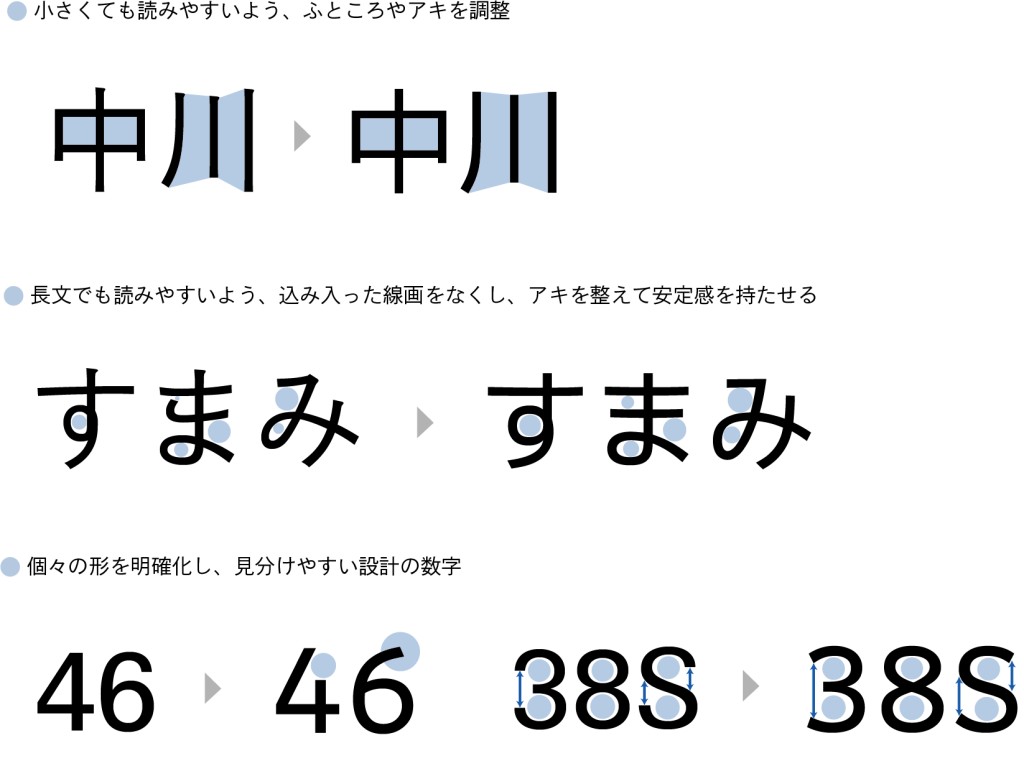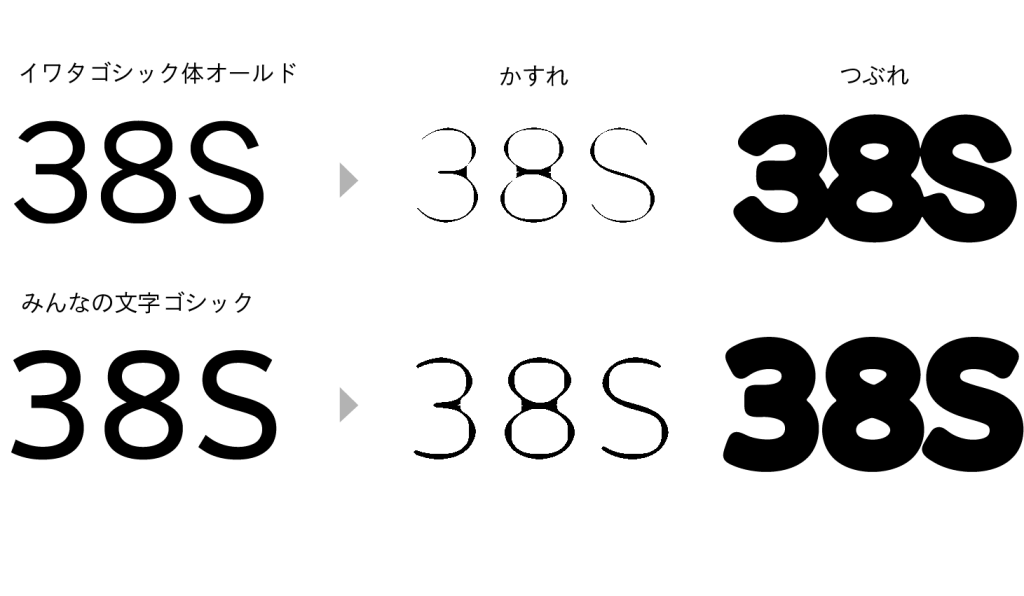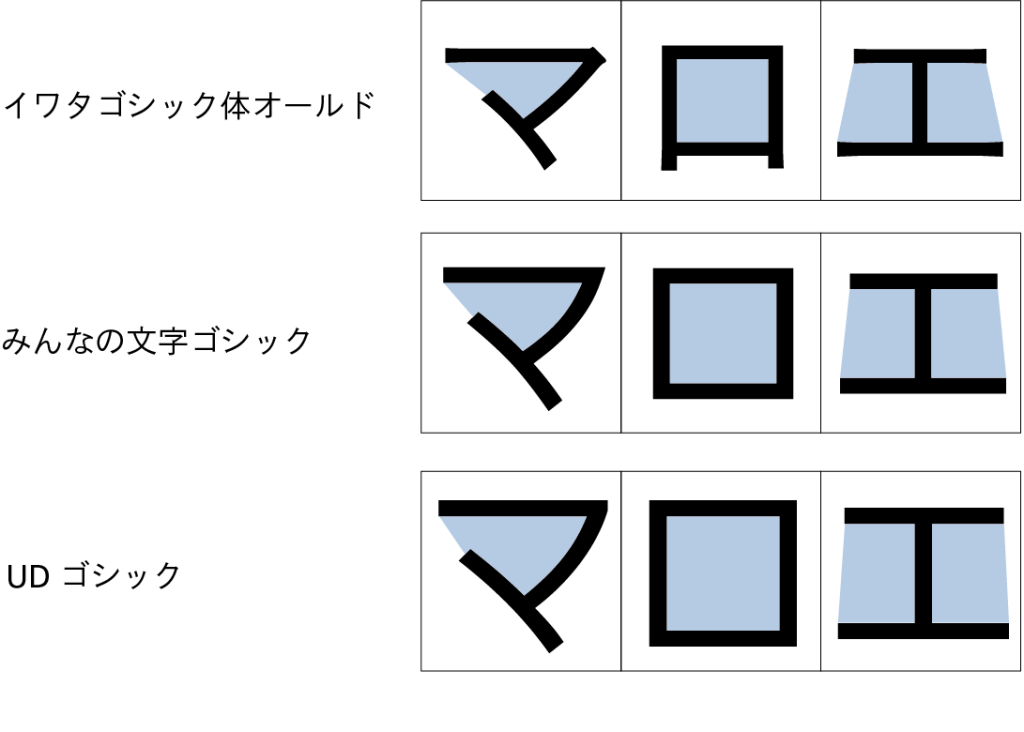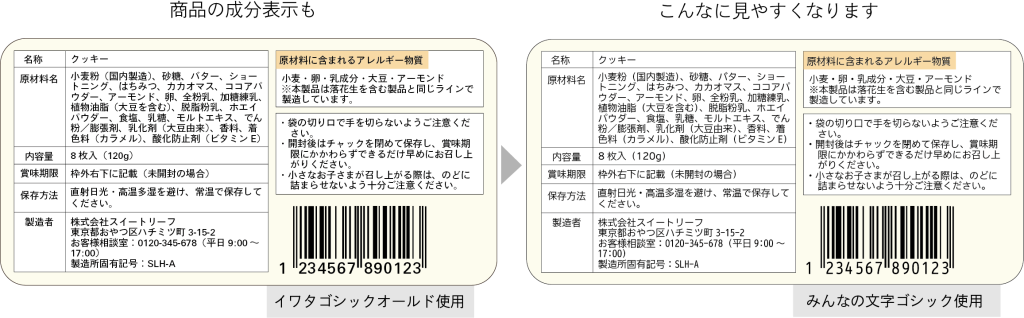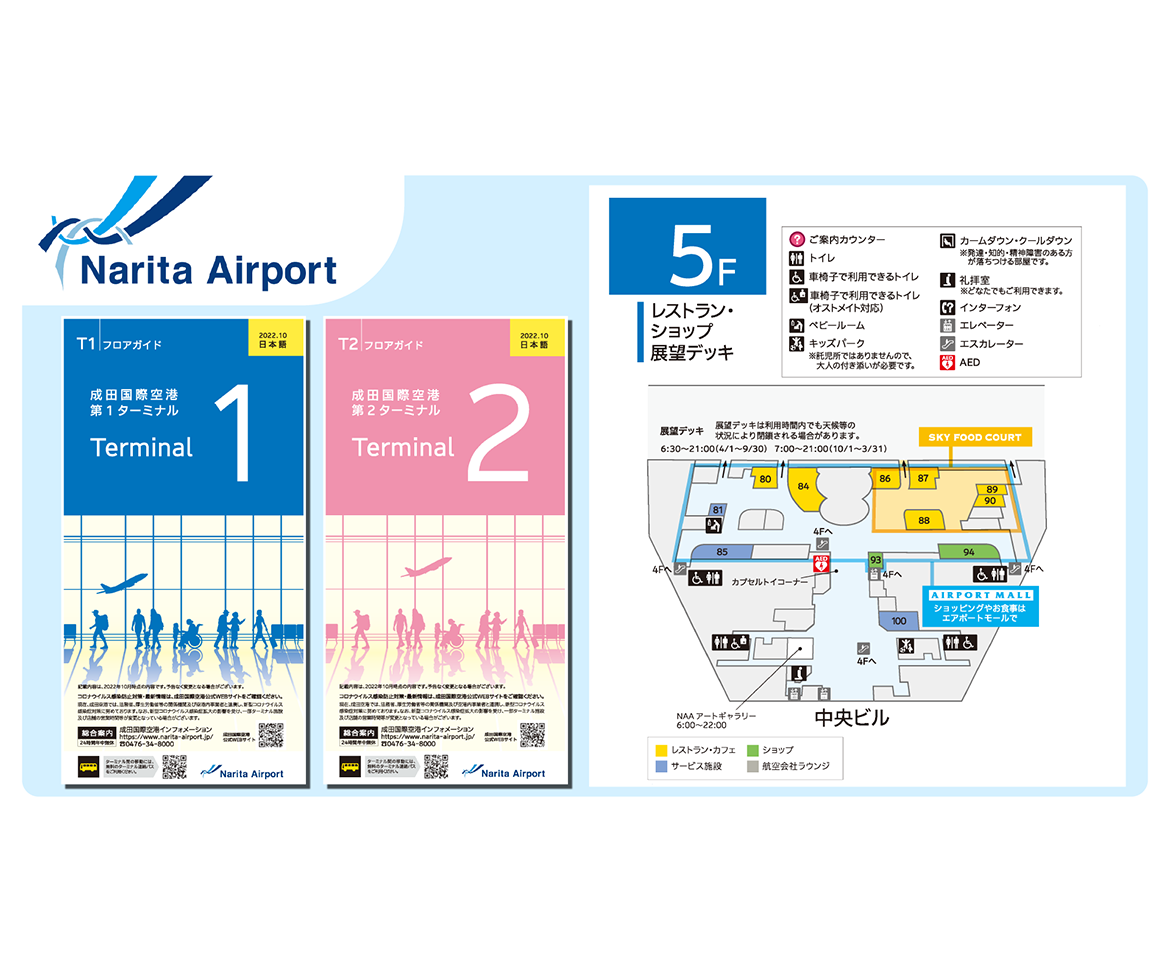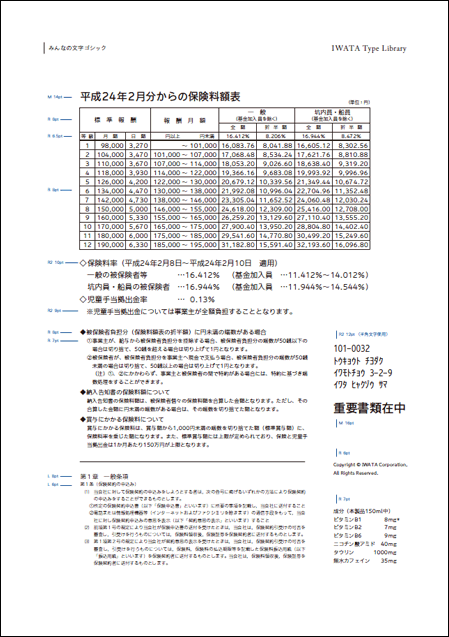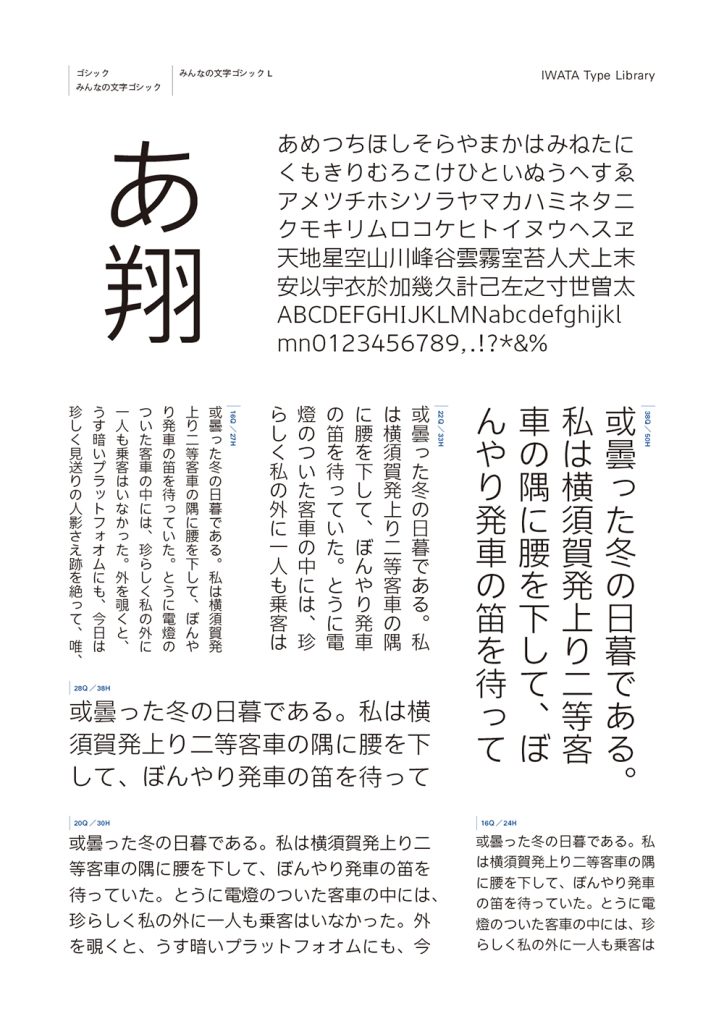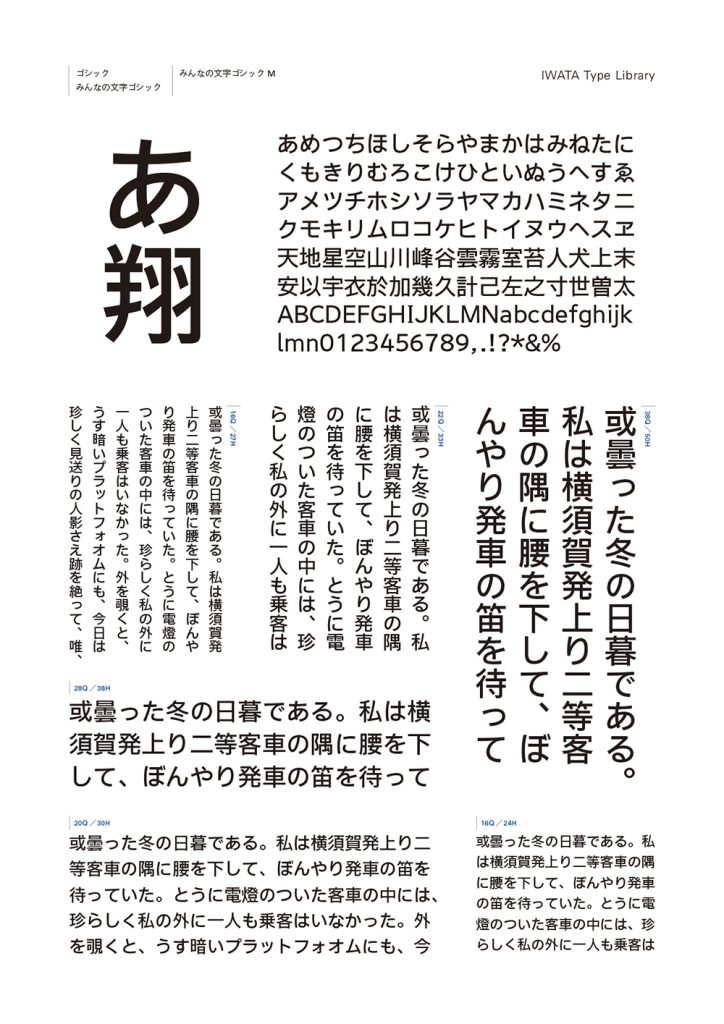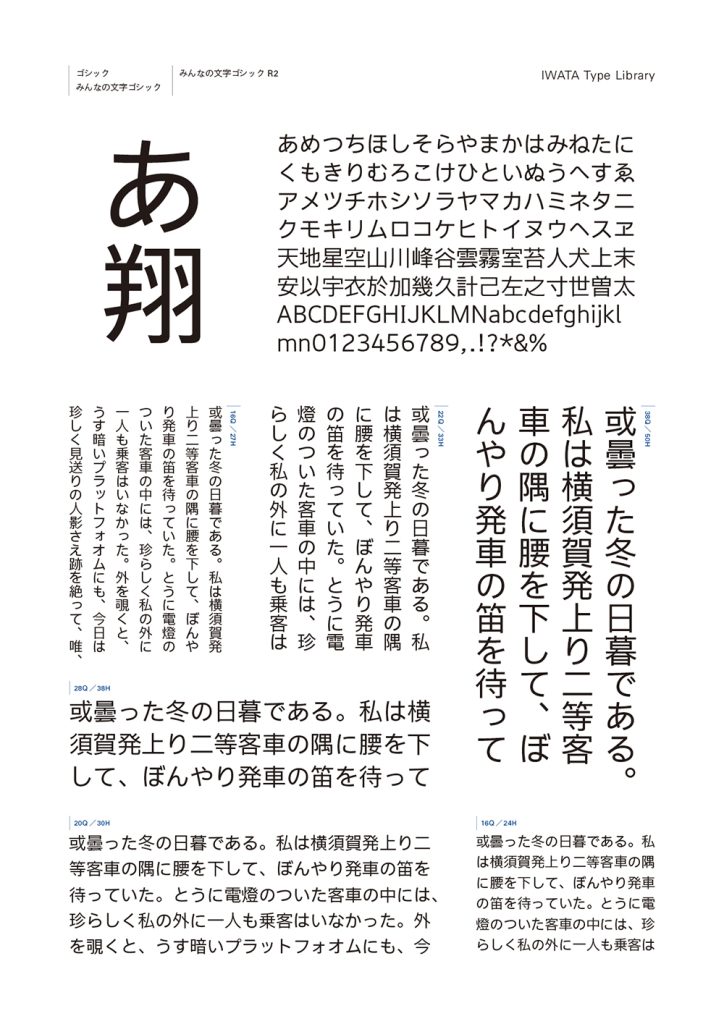
帳票や約款など、小さな文字で情報を伝える書類を読みやすくするために開発されたユニバーサルデザイン(UD)のゴシック体です。UD フォントとして唯一、第三者機関による読みやすさの認証「UCDA 認証」を取得しています。一般社団法人ユニバーサル コミュニケーション デザイン協会(UCDA)、電通、イワタの3 社共同で開発しました。
書体デザインのポイント
つぶれ・かすれ・低解像度などの劣化した環境に強く、大事な情報の誤読を防ぎます。加えて、大きくデザインしすぎないことで可読性も確保し、さまざまなシーンや幅広い年齢に対し読みやすさを維持できます。
※「イワタゴシック体オールド」と「みんなの文字ゴシック」を比較しています
開発時は、読みやすさを客観的に判断するために人間中心設計(HCD)プロセスを採り入れ、ユーザー評価と改善を繰り返し行い、さらに東京電機大学矢口式評価法(IPO テスト/特許取得済の見やすさの指標テスト)によって文字のかすれにくさやつぶれにくさを定量化しながら調整しました。これらのプロセスを踏むことでユーザビリティの高い書体を実現しています。
字面は小さすぎず大きすぎず、判読性を維持しながらより可読性を高めた設計となっています。
本文向けウェイトには、R とR2 の2 種類があります。R は7~10pt くらいで使用した際にも視認性が良好になるよう、英数字の線幅が太くなっています。R2 は10pt 以上で使用する際に仮名や漢字の見た目のバランスがよくなるよう、標準の線幅となっています。
開発の背景
老眼や白内障などの眼病の方にとって、小さな文字列を読む行為は大きなストレスとなります。特に帳票などの複雑な印刷物は、重要事項の読み間違いが問題となっています。また、医薬品の効能書き、食品の成分表などは法的規制のために文章量が多くなる傾向があります。
そのような問題を解決するために読みやすさを追求したフォントが、「みんなの文字」です。老眼や眼病の方に読みやすい文字とは、老若男女誰にとっても読みやすい文字でもあります。どんな人にでもどんな状況でも伝わりやすいデザインを「みんなの文字」が叶えます。